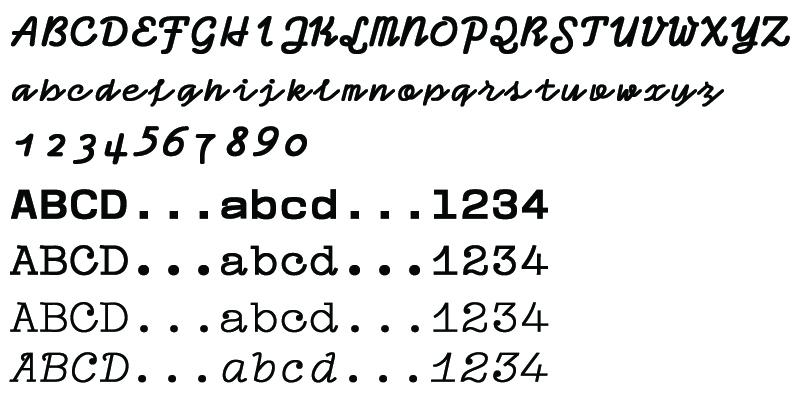
Tipografía gratuita: Compagnon, la tipografía de este mes.
La tipografía gratuita Compagnon ha sido diseñada por Juliette Duhé, Léa Pradine, Valentin Papon, Chloé Lozano y Sebastien Riollier para Velvetyne.
Un estilo neoclásico caracteriza a esta tipografía, que nos recuerda a las maquinas de escribir y la escritura a mano. Caracteres con formas muy marcadas, perfecta para dar personalidad a tus trabajos. La tipografía gratuita Compagnon es llamativa y con mucha personalidad.
Compagnon, una tipografía gratuita, diseñada por Juliette Duhé, Léa Pradine, Valentin Papon, Chloé Lozano y Sebastien Riollier está compuesta por una familia con caja alta y caja baja con los estilos Bold, Medium, Roman, Light y Light Italic.
Free typography: Compagnon, this month’s typography.
The free Compagnon typography has been designed by Juliette Duhé, Léa Pradine, Valentin Papon, Chloé Lozano and Sebastien Riollier for Velvetyne.
A neoclassical style characterizes this typography, which reminds us of typewriters and handwriting. Characters with strong shapes, perfect to give personality to your work. The free Compagnon typography is striking and full of personality.
Compagnon, a free typography, designed by Juliette Duhé, Léa Pradine, Valentin Papon, Chloé Lozano and Sebastien Riollier is composed of a family with a high and low box with the Bold, Medium, Roman, Light and Light Italic styles.